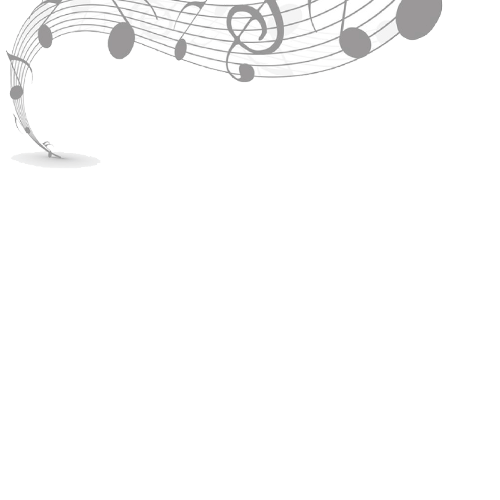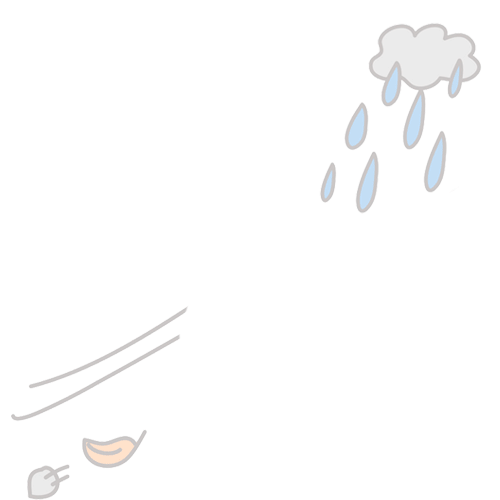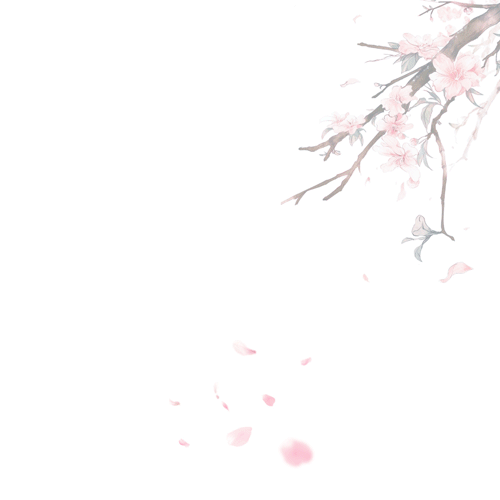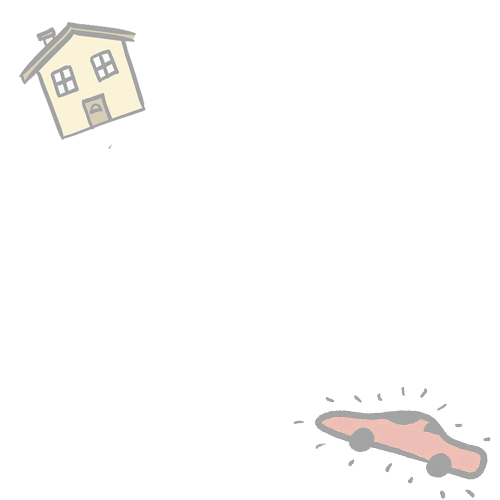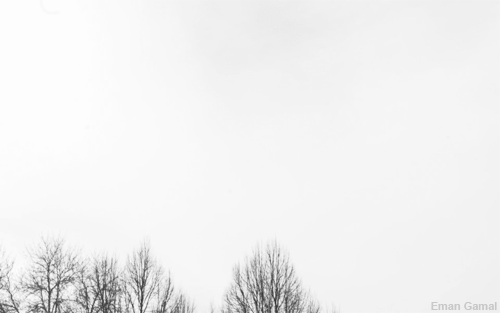
如懿传大结局了,可我忘不了的还是壹生壹次心意动
87集的如懿传终于完结了,从刚开始觉得太长追不下去,到后来觉得看不够,期待99集未删减版,观众也跟剧里的乾隆(渣渣龙)一样,对如懿万般不舍。
但花开花落自有时,至少皇帝在离世前割掉自己的头发,与如懿的断发一起放在盒子里,并带着弘历和青樱满满的回忆离去,还是成全了壹生壹次心意动的美好(这段简直让小编哭成了狗)。
还记得第一次出现这个解读,是青樱求夫妻情深,所以太后赐她“懿”字。
乾隆握着如懿的手说:
“这个懿字好啊,一次心意动。”
如懿却说:
“臣妾倒觉得,是一生一次心意动。”
从这就看出来,帝王只能给一次(曾经拥有),皇后想要的是一生(天长地久)。
ID爱自由拼音体简很好地表达这个字的含义,既是第壹次心意动,也是最后yi次。
除了《如懿传》,中国古文化中很喜欢用这种拆字,有点像暗号游戏,乍一看没什么,仔细一解读才恍然大悟,原来寓意都藏在文字中。
首当其冲的就是90、00后经常说的qiong,可以拆为“宀”、“八”、“力”,连在一起就是在固定的地方,一天卖力工作八个小时,就组成了穷,Aa小狐狸字体看起来就很形象,一种深深深深深的无力感。
而富在汉仪柏京体的表现下,一看就很有逼格,一个“宀”、一个“一”、一个“口”和一个“田”,合在一起就是一个人在固定场所,只要动动口,靠着田地就能获得财富,说白了就是要有资本,家里得有矿,才能躺着挣钱(小编只会躺,不会挣)。
其实不管是穷还是富,最重要的是“舍得”、“给予”。穷则独善其身,不给别人添烦忧,就是一种给予,达则兼济天下,造福一下别人,就是一种舍得,只有这样,才能达到一种舒心的状态,看着汉仪落花诗,我就很想躺尸了。